30 Готических шрифтов | Soohar
В данной подборке, вы найдете для себя огромное количество полезных готические шрифтов. Готический шрифт наверное является одним из самых красивых и стильных шрифтов которые можно только представить. Таинственный, чистый, а иногда и грязный вид гoтического шpифта заставляет выглядеть их более вычурными и художественными.
Взгляните на эти 30 творческих и стильных Готических шрифтов, которые можно скачать совершенно бесплатно для своих проектов. Наслаждайтесь!
Kingthings Spikeless
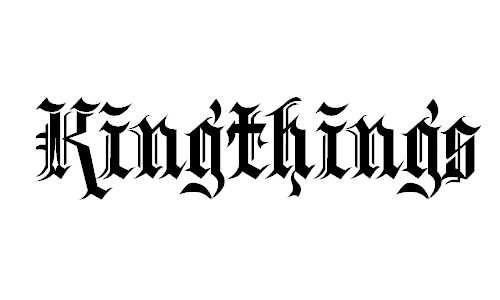
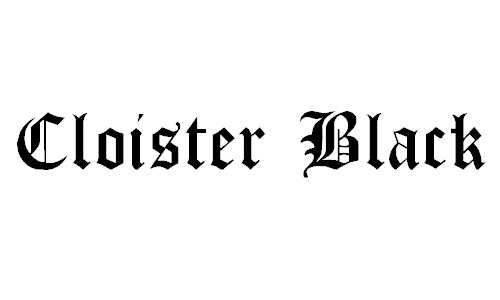
Blackletter
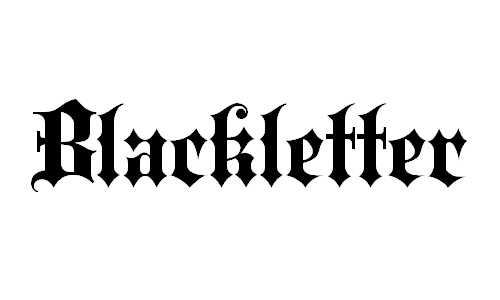
AnglicanText
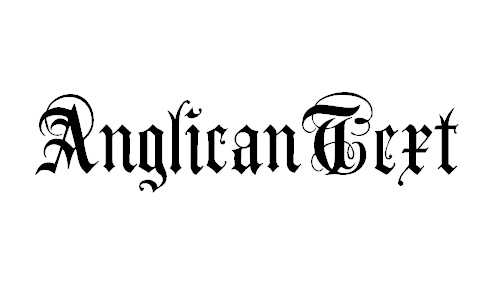
English Gothic, 17th c.
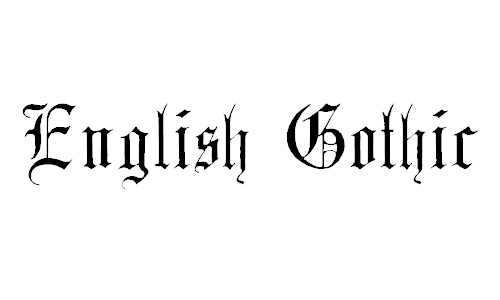
Deutsch Gothic
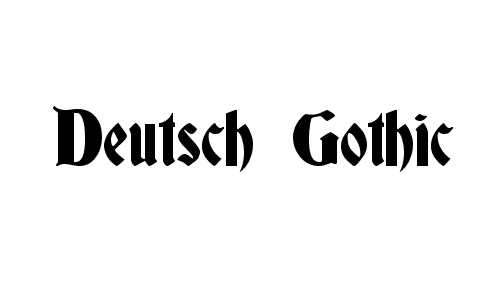
HansaGotisch
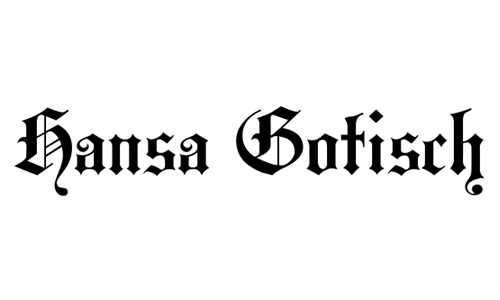
Deutsche Zierschrift
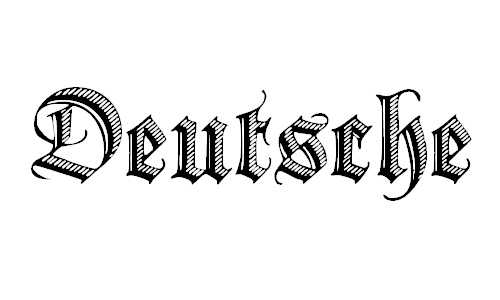
Diamond Gothic
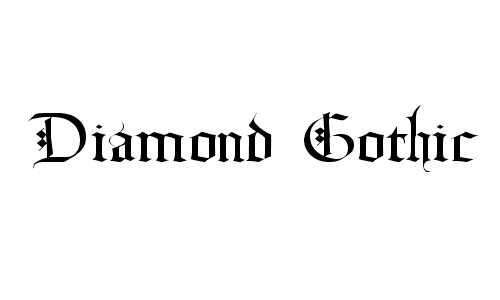
Washington Text
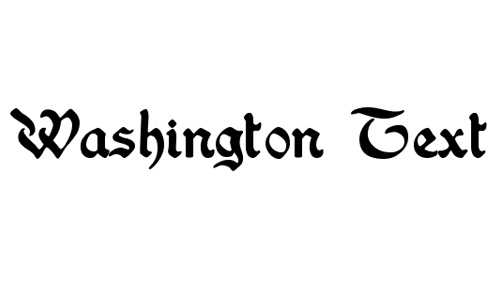
Argor Got Scaqh
Bayern
Bayreuth
Bionique
Black Castle
Boeretudor
Broken Planewing
Cantebriggia
Old London
Deadly Breakfast
Cantara Gotica
Cuxhaven Times
Dearest
Faith Collapsing
Diploma
Manuskriptgotisch
Duerers Minuskeln
A Gothique Time
Perry Gothic
target=»_blank»>Proclamate
Хэллоуин шрифт Hello ween font
Битый шрифт Black Oak
Аккуратный готический шрифт Resident Evil
Шрифт с элементами веток деревьев Wild Wood
Неровный шрифт Sin of the innoccent
Стилизованный шрифт Windswept MF
Устрашающий шрифт 13th Ghostwrite
Потекший шрифт Splywaj
Кровавый шрифт Almost Dead Bloody
Адский шрифт GhostParty
Шрифт в виде косточек 4 Dogs
Стильный шрифт BN Manson Nights
Шрифт в готическом стиле Amhole
Шрифт с узорами Vtks espinhuda
Прописной шрифт Gantz
Шрифт от руки Last N Line
Готический шрифт Carsi
Обведенный шрифт Dzr Mental
Шрифт в виде набросков Psychotic
Размазанный шрифт Convalescence
Шрифт с потертостями и потеками Cocaine Sans
Почерканный шрифт Knife Fight
Грязный шрифт с пробелами Blasphemy
Жирный грязный шрифт El&font Block